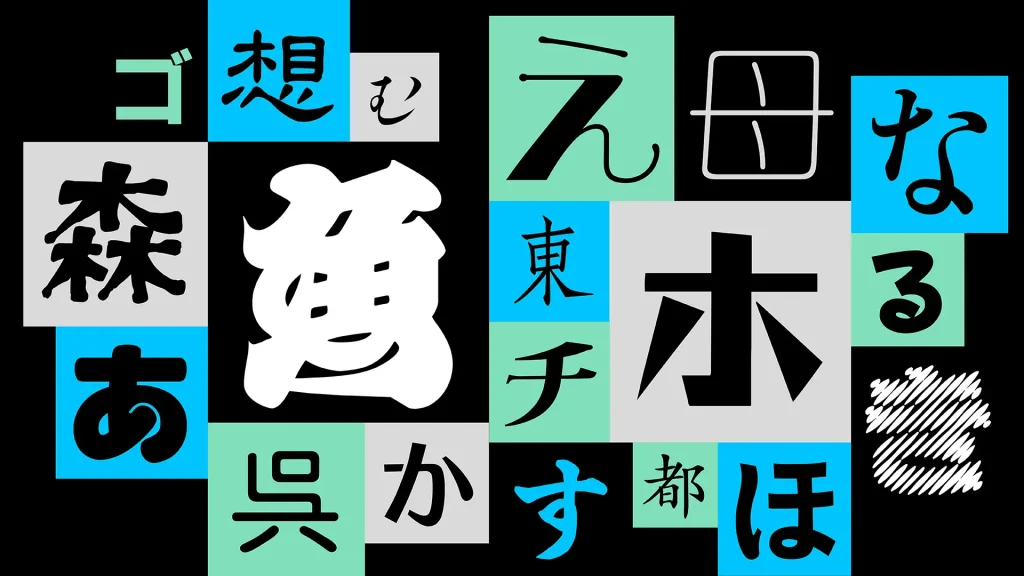
モリサワ 写研書体のOpenTypeフォント開発で今後100フォントをリリースすることを発表、邦文写真植字機発明100周年を皮切りに
株式会社モリサワは、2021年1月に発表した株式会社写研とのOpenTypeフォント開発プロジェクトにおいて、数年内に合計100フォントに及ぶリリースを予定していることを発表した。今回のリリースでは、以前に発表した改刻フォントである「石井明朝・石井明朝オールドスタイルかな」、「石井ゴシック」の13フォントと、写研のバリエーション豊かな見出し書体群を「写研クラシックス」としてOpenType化した30フォント、合計43フォントを2024年に提供する。そして2025年以降も、これらに続くラインナップを順次提供予定。
「写研クラシックス」は、多種多様な名作見出し書体群が、写植全盛期の味わい深いデザインそのままにお使いいただけるフォント。写研から提供を受けたアウトラインデータに加え、不足文字の作成、文字セットなどの仕様の整理を行った。見出し利用に特化させ、従来写真植字機でのみ利用可能だった多くの写研書体と、写真植字機時代に発表されていない書体を、現代のOpenTypeフォントとして再現したもの。
<2024年に提供開始を予定しているフォント>
改刻フォント
石井明朝 L / R / M / B
石井明朝オールドスタイルかな L / R / M / B
石井ゴシック L / R / M / B / EB
写研クラシックス
有行書
石井楷書
石井中ゴシック
石井中丸ゴシック
石井中明朝
石井中明朝オールドスタイル大がな
イナクズレ
イナピエロ B
イナミン
イノフリー
いまぎょう
今宋
いまりゅう
織田特太楷書
ゴーシャ E
紅蘭中楷書
ゴカール H
ゴナ E
新聞特太ゴシック
新聞特太明朝
創挙蘭 E
曽蘭太隷書
スーシャ H
スーボ B
鈴江戸
ナール EL / E
ナミン
ボカッシイG
ミンカール